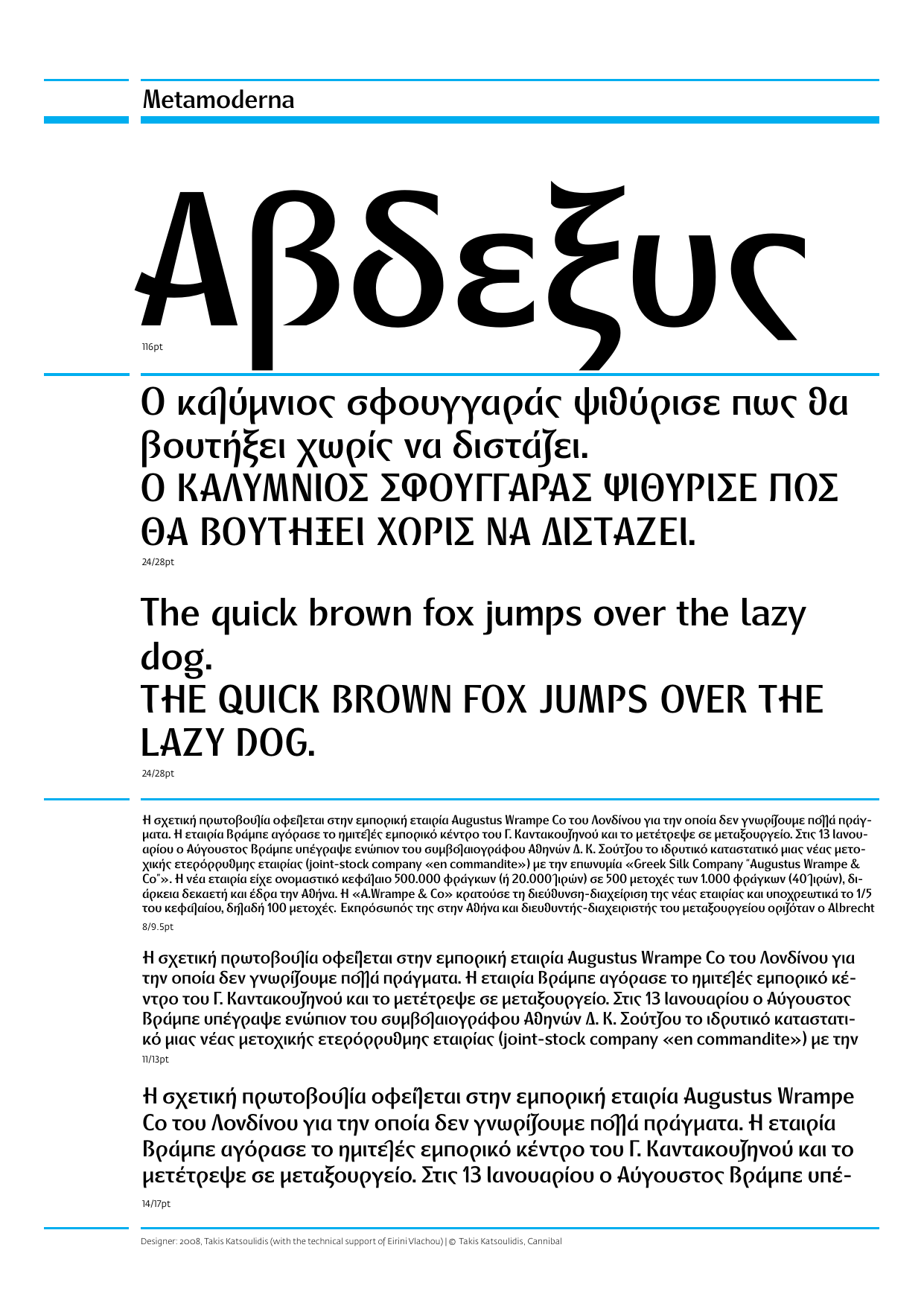
Metamoderna
Τάκης Κατσουλίδης: Μετά από μερικές δεκαετίες σχεδιασμού τυπογραφικών γραμμάτων επιχείρησα να δημιουργήσω μία ανισόπαχη γραμματοσειρά που βγαίνει από παρατηρήσεις της σύγχρονης χειρόγραφης Ελληνικής γραφής χωρίς καλλιγραφικές φιοριτούρες. Η καινοτομία είναι κυρίως στο σχέδιο του λάμδα όπου κατήργησα το μπροστινό σκέλος του, το οποίο απωθούσε το προηγούμενο γράμμα αφήνοντας ένα κενό, σχεδίασα το βασικό στέλεχος του γράμματος κάθετο να προεξέχει επάνω και κάτω από τον οφθαλμό των άλλων στοιχείων έτσι που να μην χάνει το χαρακτήρα του. Επίσης το ζήτα σχεδιάστηκε σε κάθετη μορφή έτσι που να μην αφήνει το άσπρο κενό δεξιά του. Τέλος στο κεφαλαίο Ωμέγα έγινε μια σημαντική απλοποίηση χωρίς να χάσει το βασικό του σχέδιο. Είναι ένα αλφάβητο στο οποίο κυριαρχεί η καμπύλη και είναι διαθέσιμο σε 4 όρθια, πλάγια, με Ελληνικό Μονοτονικό, Πολυτονικό και πλήρες Λατινικό και Κεντρο-Ευρωπαϊκό σετ.